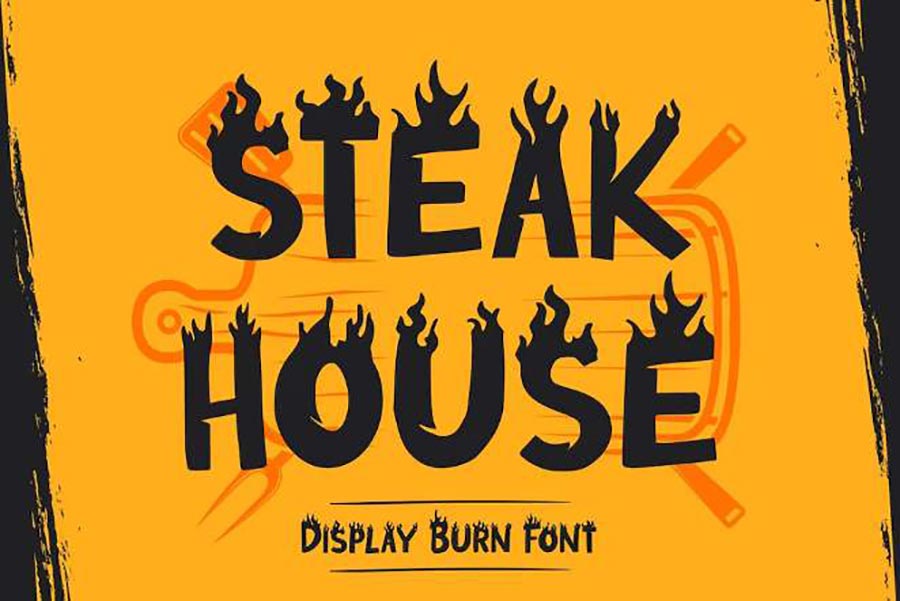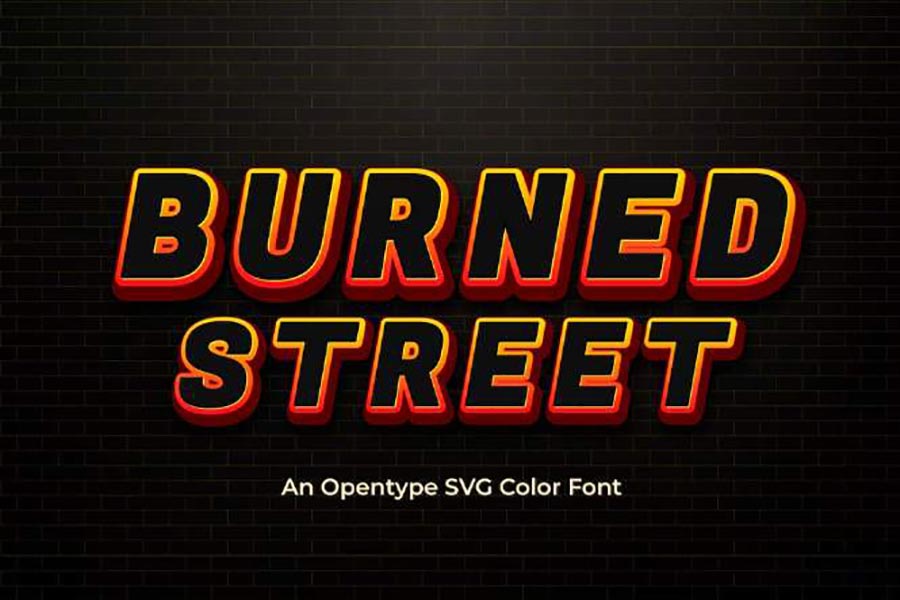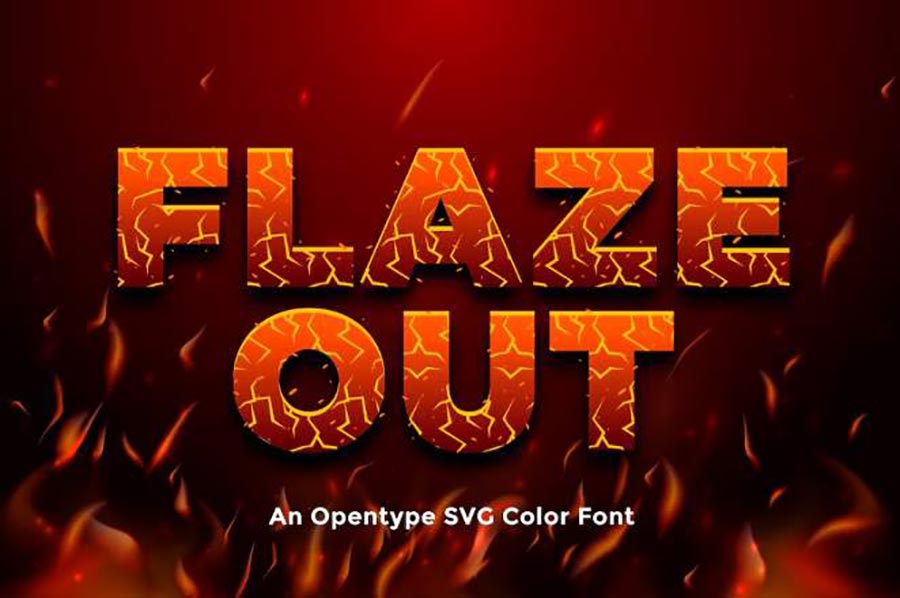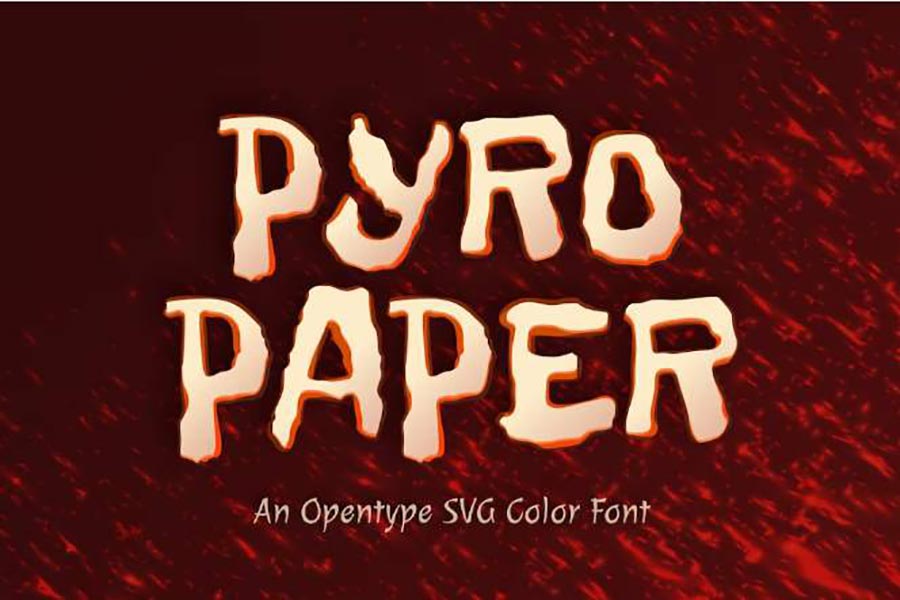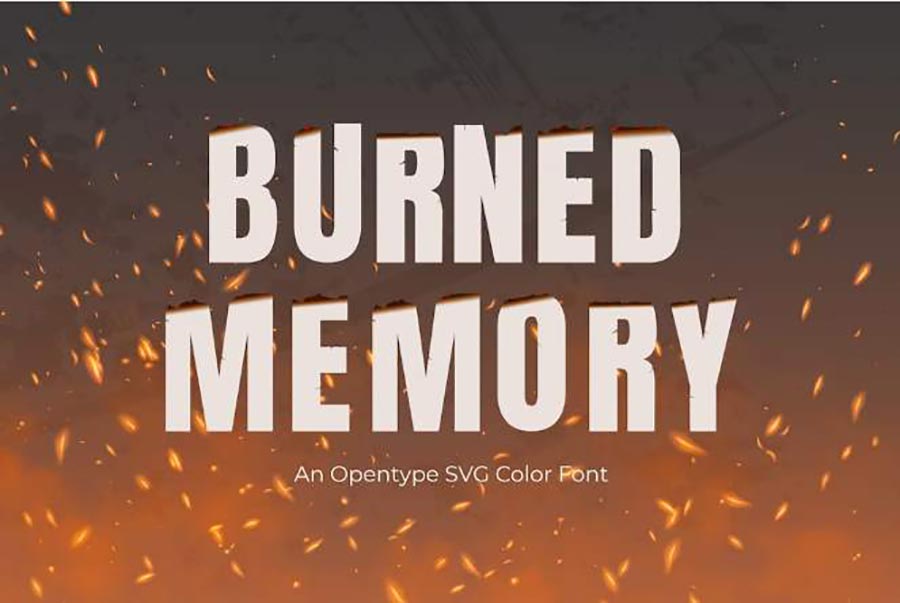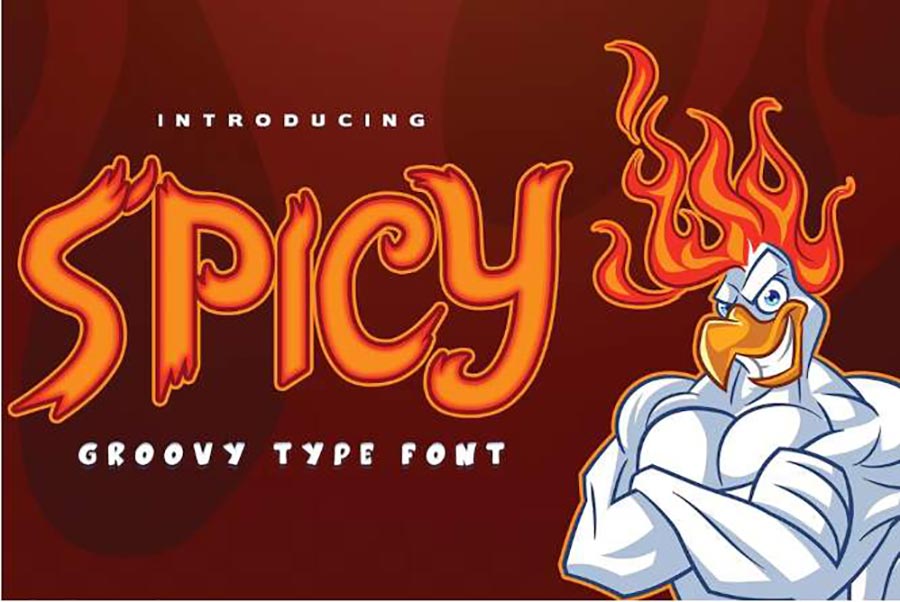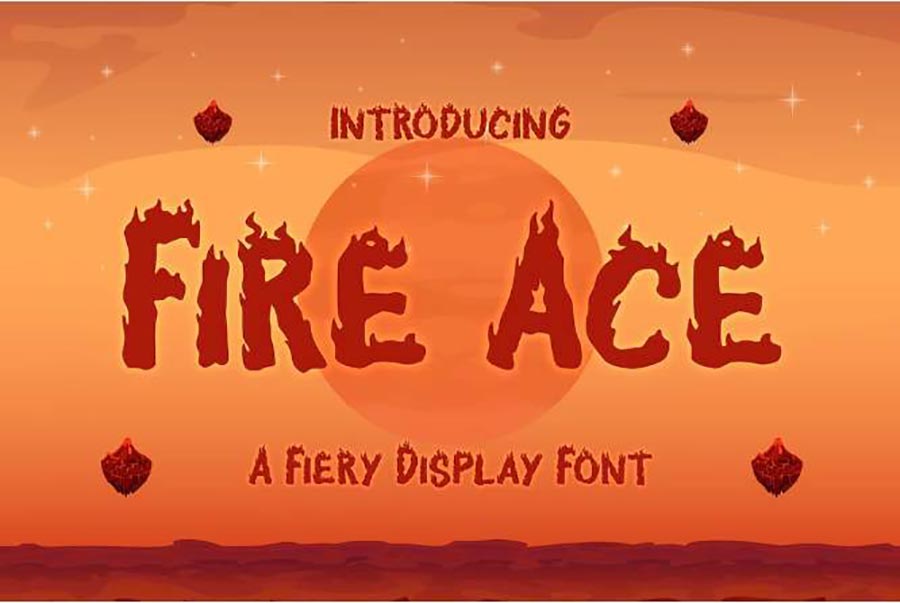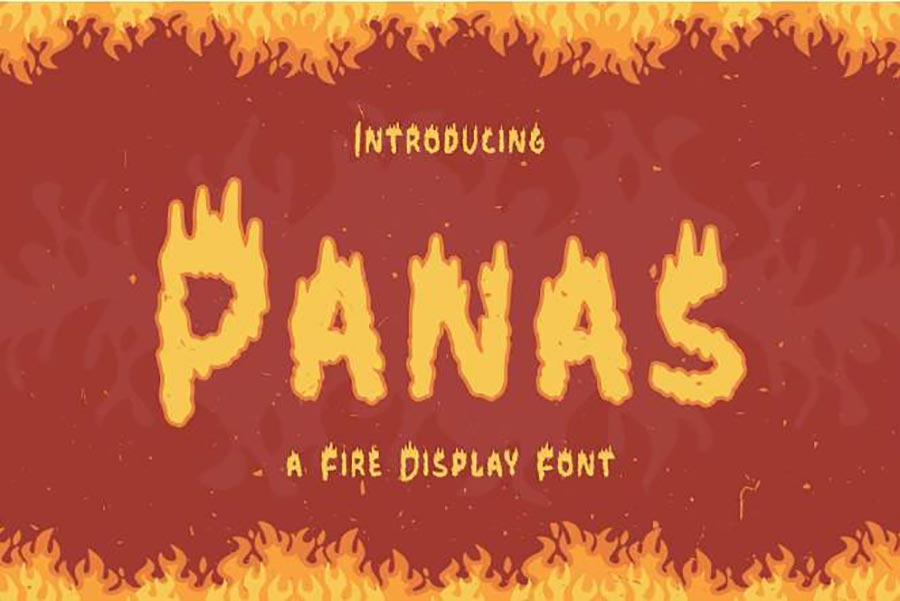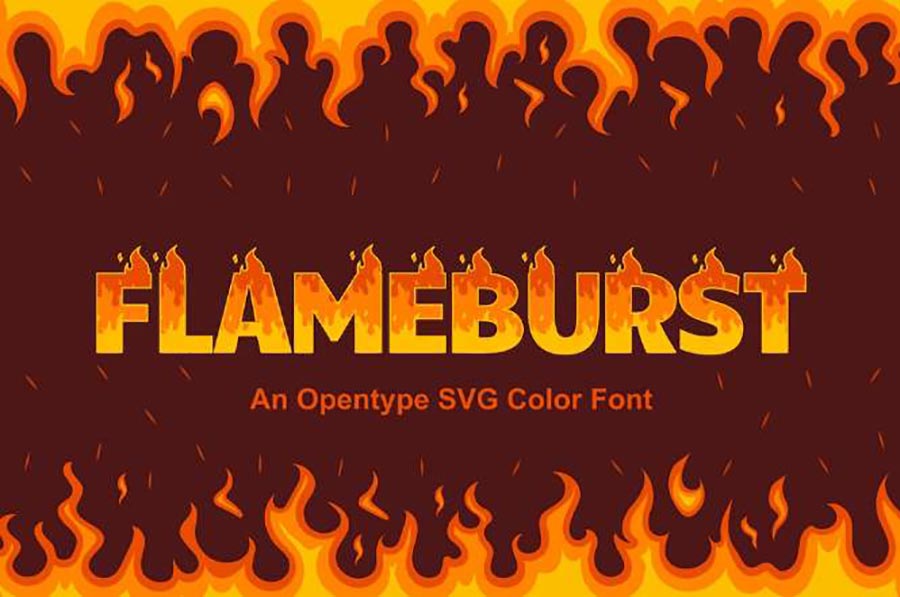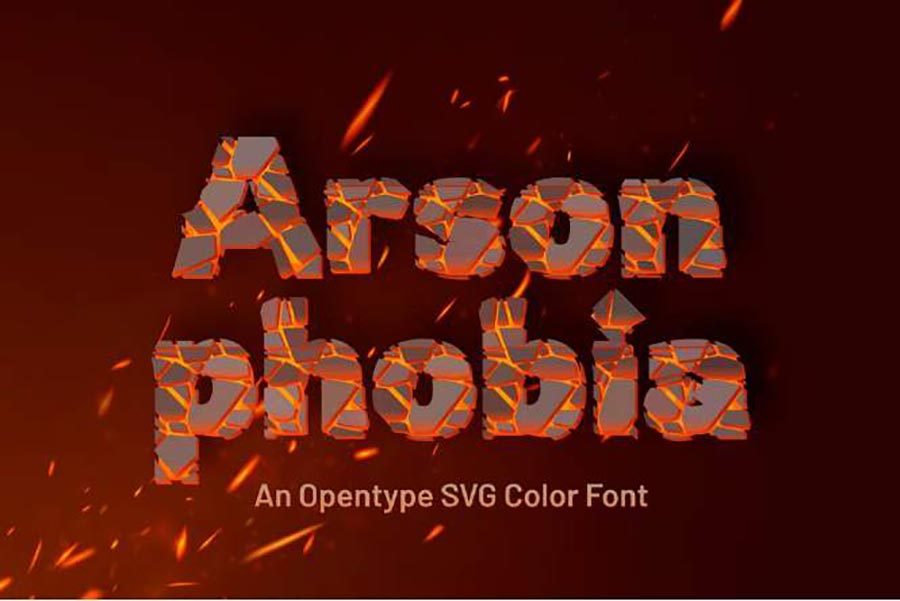
Font chữ luôn là yếu tố quan trọng giúp nâng cao giá trị thẩm mỹ và sự chuyên nghiệp trong thiết kế. Trong đó, font chữ lửa với phong cách mạnh mẽ, cá tính và đầy sáng tạo đang trở thành xu hướng được nhiều designer yêu thích. Nếu bạn đang tìm kiếm một bộ font chữ lửa đẹp mắt và hoàn toàn miễn phí, hãy để sadesign.vn giúp bạn. Bài viết này sẽ hướng dẫn chi tiết cách tải xuống bộ 15+ font chữ lửa tuyệt đẹp từ sadesign.vn một cách dễ dàng và nhanh chóng.
Tại Sao Nên Sử Dụng Font Chữ Lửa Trong Thiết Kế?
Font chữ lửa không chỉ mang lại sự nổi bật mà còn tạo điểm nhấn mạnh mẽ cho các dự án thiết kế. Với hiệu ứng cháy rực rỡ, các font chữ này thường được sử dụng trong các lĩnh vực như quảng cáo, poster sự kiện, game design hoặc các dự án đòi hỏi phong cách cá tính, năng động.
Sự độc đáo của những font chữ lửa nằm ở khả năng truyền tải cảm xúc mạnh mẽ, kích thích thị giác và tạo ấn tượng khó quên cho người xem. Đặc biệt, với bộ font chữ lửa từ sadesign.vn, bạn sẽ có thêm nhiều sự lựa chọn để sáng tạo không giới hạn.
Một Số Lưu Ý Khi Sử Dụng Font Chữ Lửa
- Kết Hợp Sáng Tạo: Font chữ lửa thường rất nổi bật, vì vậy hãy kết hợp chúng với các yếu tố thiết kế khác một cách hài hòa để tránh làm rối mắt người xem.
- Kiểm Tra Độ Phù Hợp: Không phải dự án nào cũng phù hợp với phong cách mạnh mẽ của font chữ lửa. Hãy cân nhắc lựa chọn font phù hợp với thông điệp mà bạn muốn truyền tải.
Một số thiết kế trong bộ 15+ font chữ lửa miễn phí từ sadesign.vn